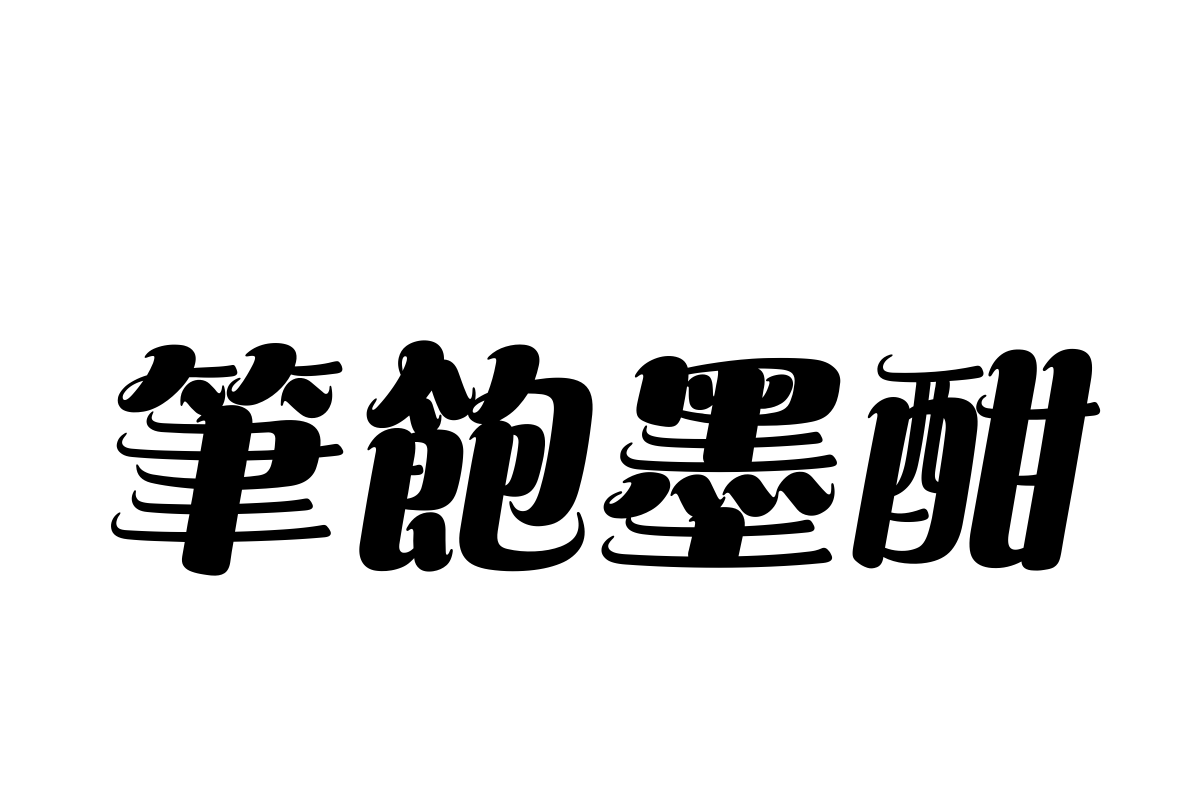
汉仪花仙子繁体字体是一款专为中文排版设计的字体,具有独特的艺术风格和设计感。这款字体采用了现代的设计手法,将传统汉字与现代元素相结合,使得字体更加时尚、独特。
汉仪花仙子繁体字体的特点如下:
1. 字形优美:汉仪花仙子繁体字体的字形线条流畅,结构紧凑,呈现出一种优雅的艺术美感。这种美感使得字体在视觉上具有较高的吸引力,能够更好地传达文字内容。
2. 笔画细腻:汉仪花仙子繁体字体的笔画精细,每个字的笔画都经过精心设计,使得字体更加精致。这种细腻的笔画使得字体在阅读时更加舒适,不易产生疲劳感。
3. 设计风格独特:汉仪花仙子繁体字体采用了独特的设计风格,将传统汉字与现代元素相结合,使得字体具有很高的辨识度。这种独特的设计风格使得字体在众多字体中脱颖而出,成为一款独具特色的字体。
4. 适用范围广泛:汉仪花仙子繁体字体适用于各种类型的文本排版,如书籍、杂志、报纸、广告等。无论是正式的文件还是创意的文案,汉仪花仙子繁体字体都能提供良好的视觉效果,满足不同场合的需求。
总之,汉仪花仙子繁体字体是一款具有独特艺术风格和设计感的字体,适合用于各类文本排版。它的线条流畅、笔画细腻、设计风格独特等特点使得字体在视觉上具有较高的吸引力,能够更好地传达文字内容。